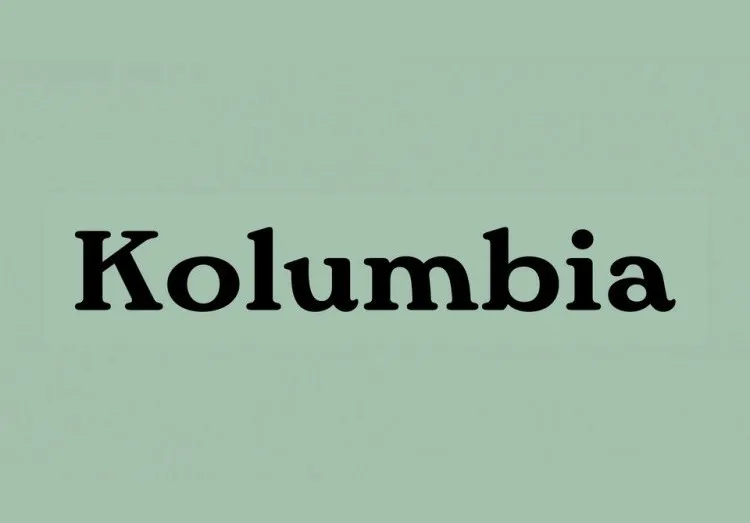
A Columbia é uma elegante fónta serif que vem do estilo Columbia, originário dos EUA, mas adaptado para intersecções entre os anos 20 e 30 no contexto polonês. Criada pela artesãos Ania Wieluńska e Borys Kosmynka em uma mistura de influências modernas e clássicas, esta fónta foi originalmente projetada como uma versão simplificada do Post Oldstyle Roman, um dos estilos typográficos mais conhecidos da época. Este tipo de letra é perfeitamente adequado para textos formais ou corporativos, transmitindo um tom elegante e sofisticado que se adapta bem a diversos usos, desde contratos profissionais até capas de livros ou gráficos publicitários. A versão Columbia da fónta está disponível através das duas principais foundries poloneses em época do interwar – Jeżyński e Idźkowski –, sob o nome originalmente atribuído ao tipo: Kolonial e Columbia. Este é um exemplo fascinante de como estilos typográficos que eram concebidos inicialmente para um público americano podem ser re-interpretados e adaptados para diferentes culturas e contextos linguísticos.